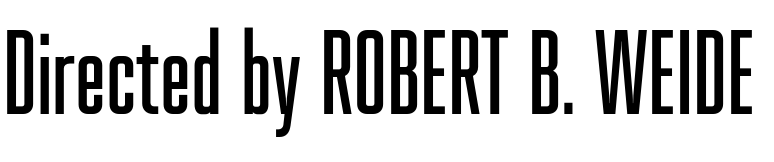
146 fonts · collected by Yevgen Sadko
Це добірка кириличних веб-шрифтів з України і всього світу, окрім росії. Шрифти підходять для інтернет-магазинів тактичного спорядження і товарів армійської та військової тематики. Також цими шрифтами можна робити написи на шевронах, прапорах, емблемах і нагородах. Складено спеціально для українського конструктору сайтів Weblium.